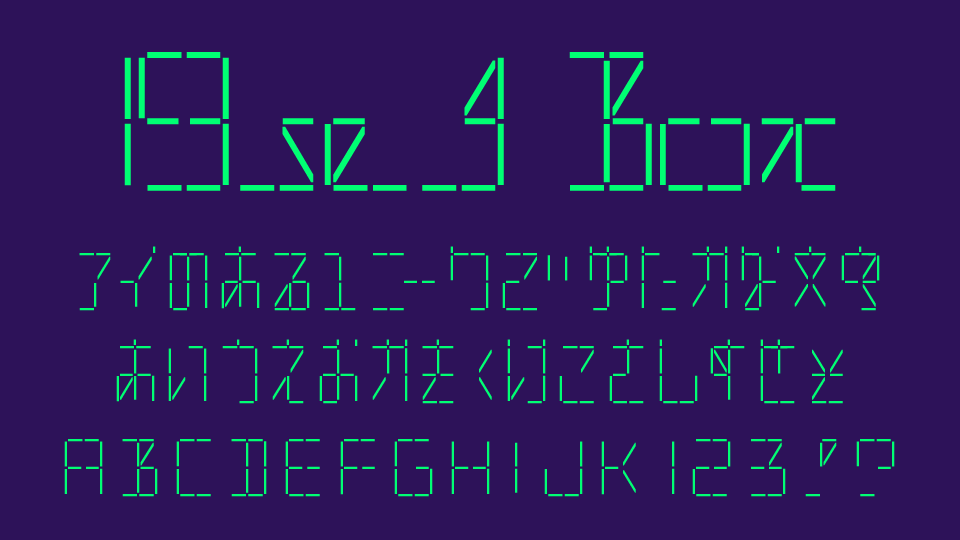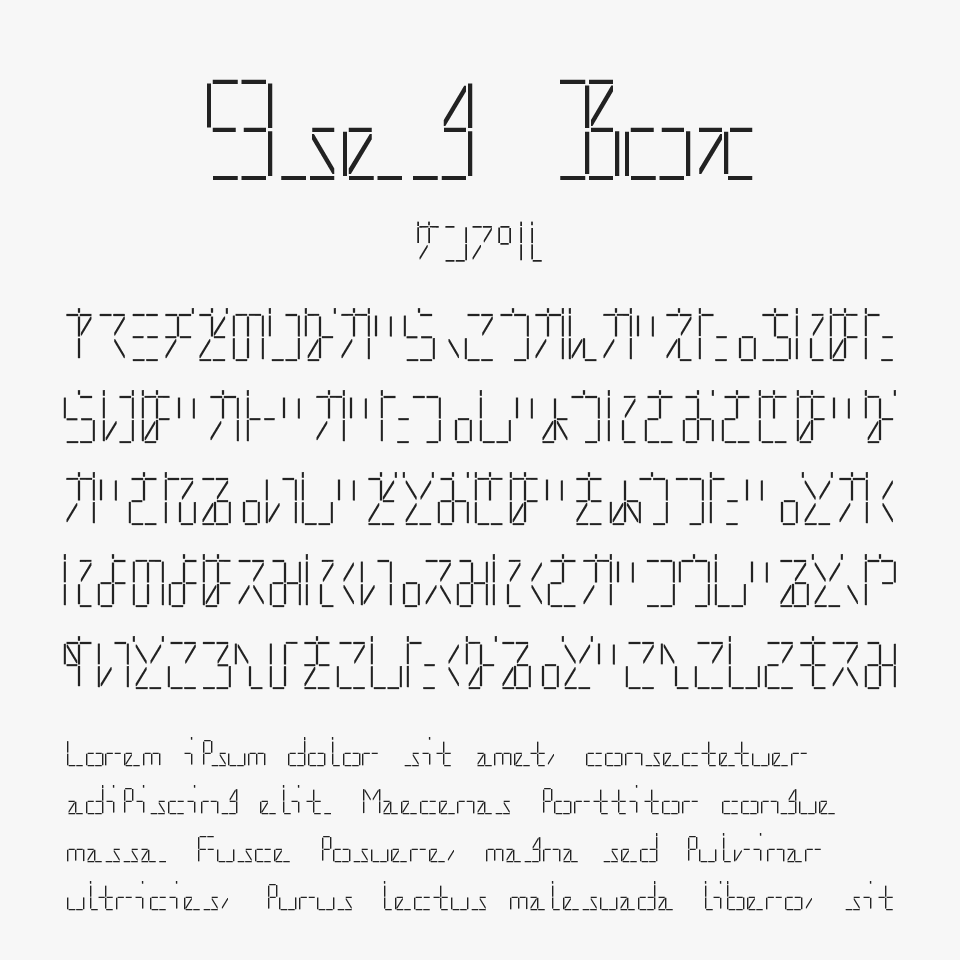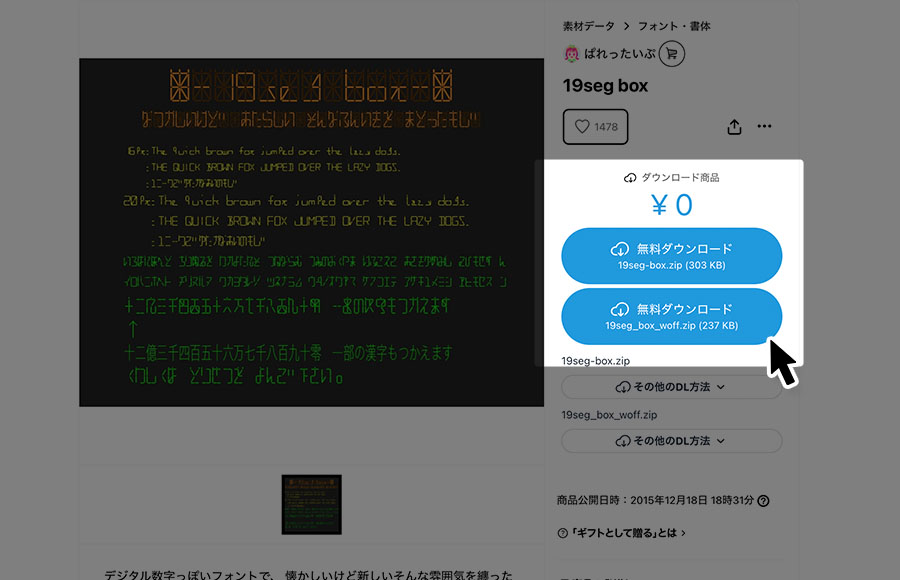
19seg Boxフォントは、電光掲示板のような19セグメントディスプレイを思わせる細いラインだけで構成されたデジタル風デザインフォントです。
格子状の構造を活かした文字は、電光掲示板やレトロな電子機器や近未来のインターフェースを連想させる独特な雰囲気が感じられるフォントです。細身で軽やかな見た目ながら、一文字ごとの個性が際立ち、タイトルやロゴに取り入れるだけで印象的なデザインに仕上がります。
SF作品やゲーム、サイバーな世界観、ガジェット関連のデザイン、イベントロゴ、YouTubeサムネイルなどにおすすめです。線だけで構成されたシンプルなデザインなので、背景や演出次第でレトロにも未来的にも使い分けられるフォントです。
19seg Box